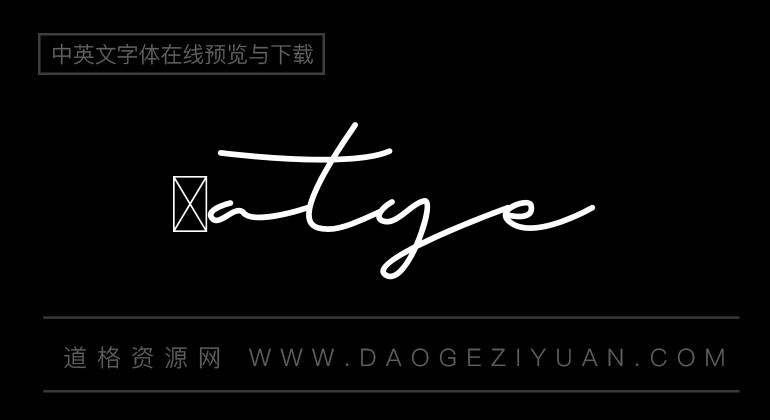
Fatye 字体是一款具有新颖、可爱、可玩性的易读字体,它有着独特的可爱风格,可以用于给文字增添一份可爱的气息,令文字更加生动有趣。Fatye 字体有着清晰的线条,字体的曲线可以把文字和图案结合在一起,形成一个统一的整体,使得文字更加精致、活泼、可爱。内容介绍
Fatye是一款非常不错的手写艺术字体,具有很好的视觉感,适合于文化类的宣传设计、商业类品牌的广告和产品包装设计以及个性化文字排版等较多场景。